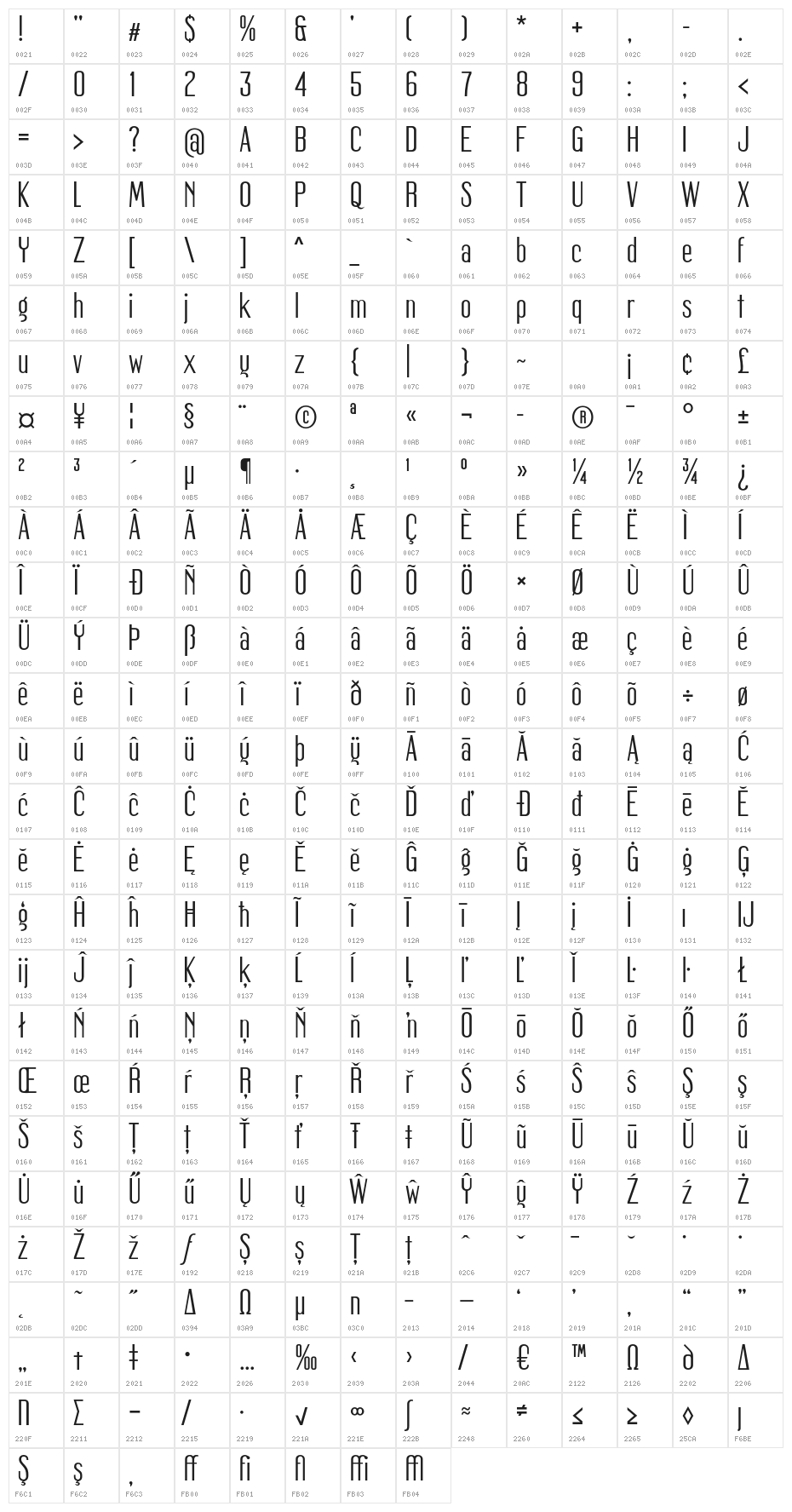
Mager Font
| Anwendungsfall | Headlines, Body text, Logos |
| Vorgeschlagene Projekte | Ideal for branding, editorial design, and digital interfaces where a modern and clean aesthetic is desired. |